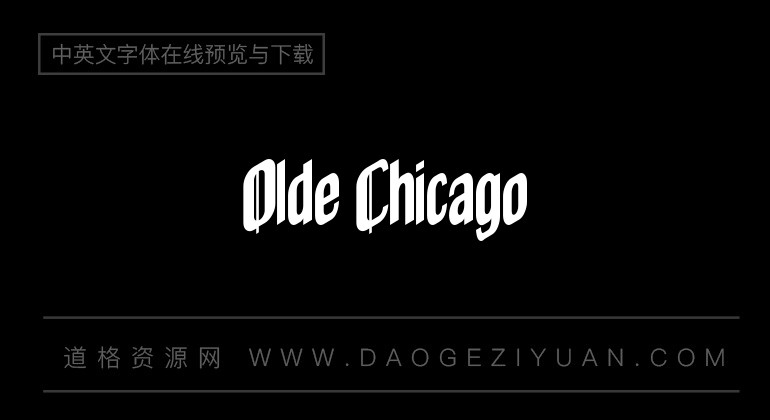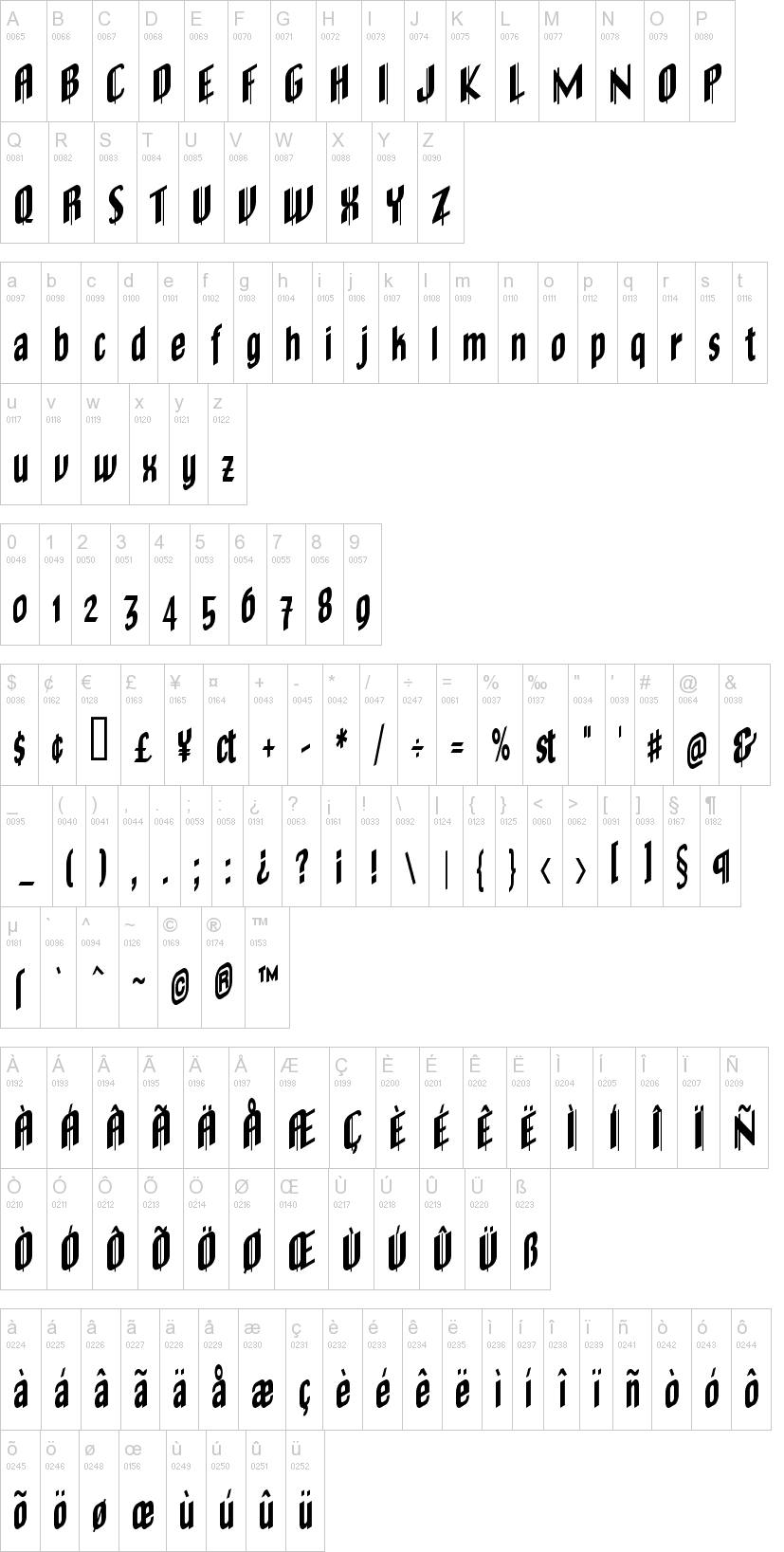
Olde Chicago 字体是一种明亮而粗犷的西方字体,它以20世纪20年代的芝加哥为背景,融合了街头文化的元素,具有独特的复古风格。Olde Chicago 字体的字符具有粗犷的外观,并具有宽度和高度的不对称性,以及横向的粗细变化,使得字体看起来更有质感。Olde Chicago 字体适合用于标签,海报,书籍和品牌设计,可以为设计师提供独特的复古风格。内容介绍
Olde Chicago是一款非常不错的手写艺术字体,具有很好的视觉感,适合于文化类的宣传设计、商业类品牌的广告和产品包装设计以及个性化文字排版等较多场景。